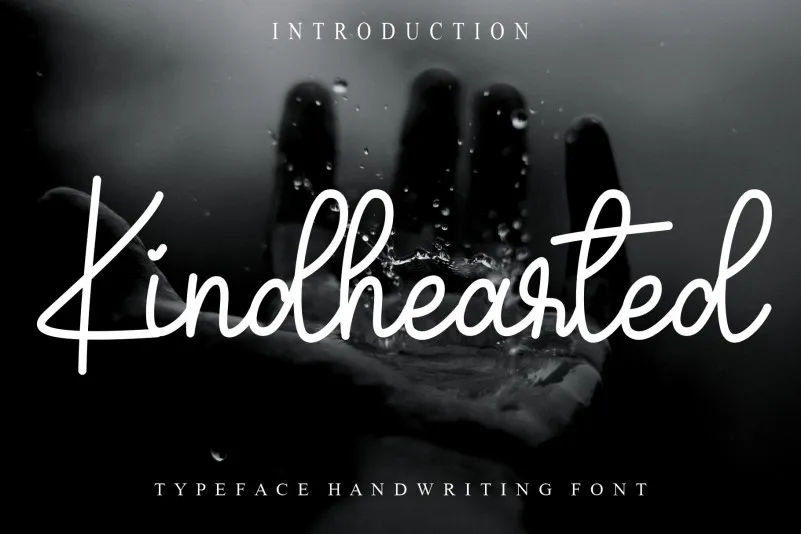
Aqui está uma descrição envolvente e natural para a página de download da fonte Kindhearted Handwritten Font: A Kindhearted Handwritten Font é mais do que simplesmente um conjunto de letras, ela transmite sentimentos únicos através das linhas suaves e sutis. Desenhada por CreativeLetter com carinho, esta fonte expressa uma variedade de emoções através da forma quase autêntica dos gestos humanos, criando a sensação de comunicação direta entre os escritores e leitores. Ideal para criação de designs que envolvem emoção e conexão humana, essa fonte oferece nuances perfeitas. Ela é especialmente adequada para cartas pessoais, mensagens íntimas, anúncios emocionantes ou qualquer outro tipo de conteúdo que busque expressar sentimentos profundos através do texto. A Kindhearted Handwritten Font não apenas adicionará um toque delicado a seus projetos gráficos, mas também os tornará únicos e verdadeiramente humanos. Esta fonte é perfeita para aqueles buscando algo mais além da simples transcrição de texto. Com uma escrita genuína e emotiva, ela oferece uma maneira única de expressar sua própria voz e criar uma conexão verdadeira entre o espectador e o design.